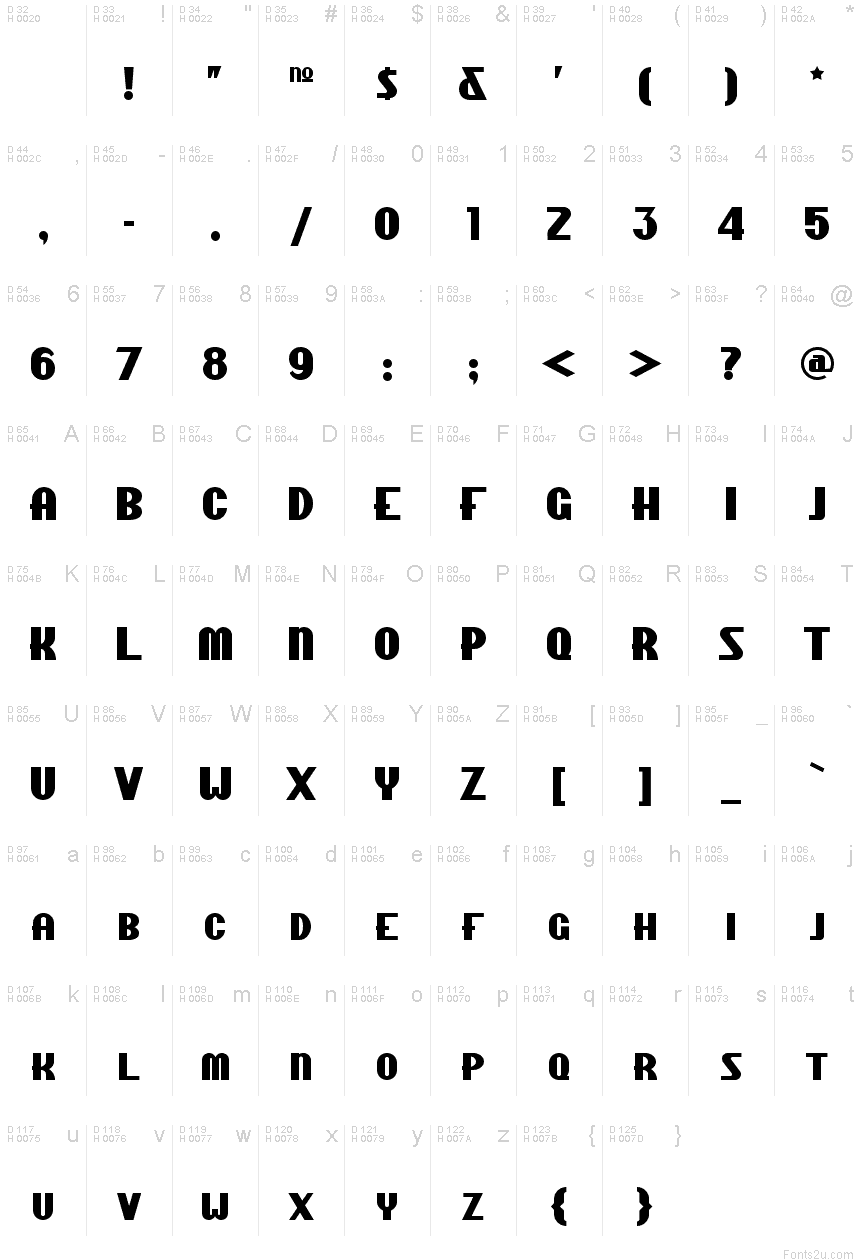
ChippewaFallsNF 字体
ChippewaFallsNF
Nick's Fonts
Nick Curtis
Chippewa Falls NF 是由 Nick Curtis 设计的一款免费复古展示字体。其厚重、方正的笔画结构配合圆润的边角,经由锐利的垂直切口处理,赋予了每个字母一种充满力量感、近乎机械的节奏。整体风格让人联想到古老的木刻海报和老式工厂招牌——大胆、紧凑,专为在远处也能引人注目而生。
使用 Chippewa Falls NF,您的标题在海报、活动传单、饮料标签、醒目 Logo、店铺招牌及 T 恤印花上都能瞬间抓住视线。这款免费字体在字号较大时表现最为出色,其厚重的笔画和紧凑的字间距能在版面上产生极强的视觉冲击力。在正文中使用干净的几何无衬线字体与它搭配,让 Chippewa FallsNF 成为那些最需要展现个性的高光时刻。